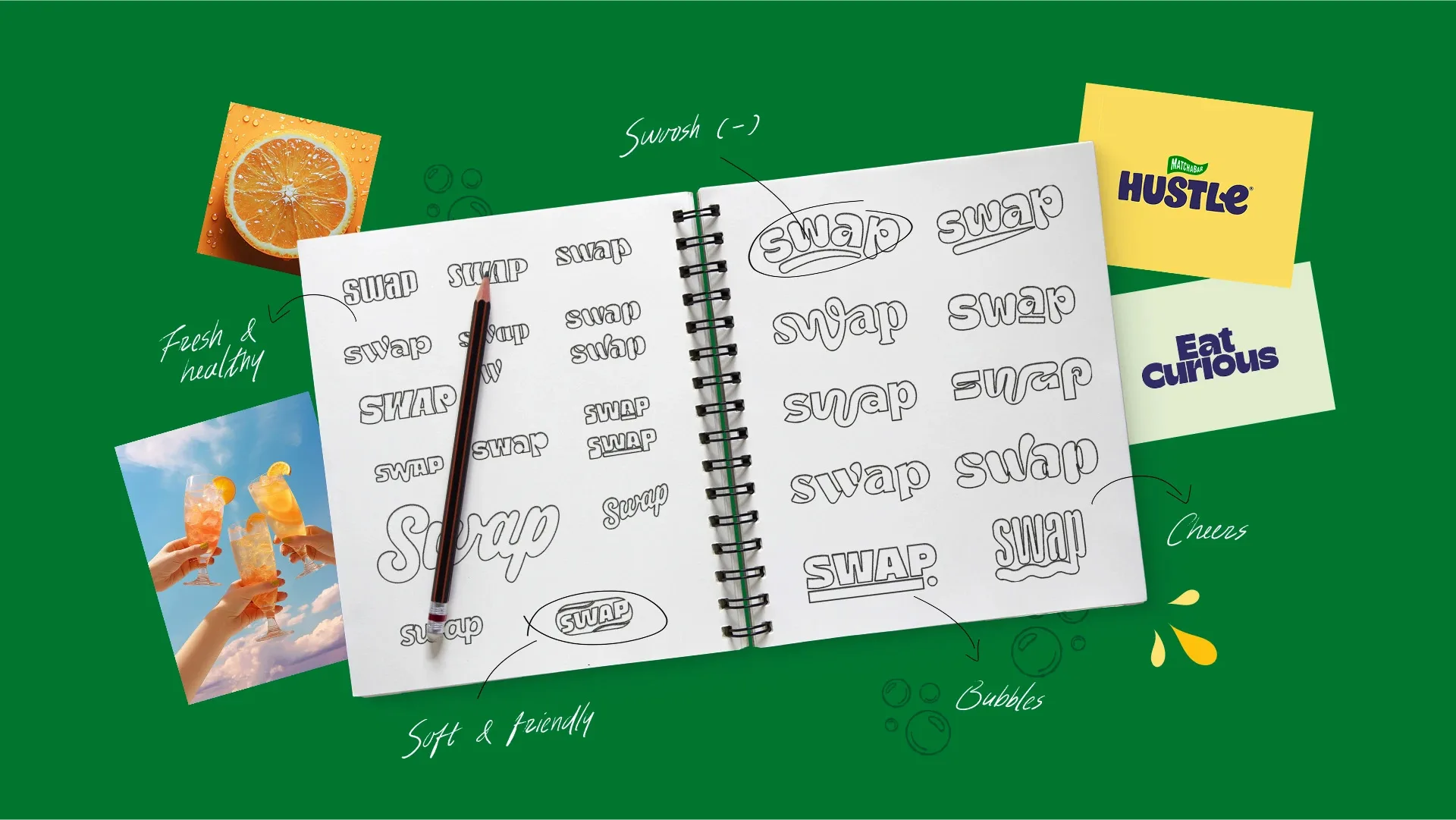
Trong thế giới thiết kế đồ họa, typography không chỉ là việc chọn font chữ đẹp mà còn là nghệ thuật kể chuyện thương hiệu. Đặc biệt trong thiết kế bao bì, font chữ có thể quyết định liệu sản phẩm của bạn có nổi bật trên kệ hàng hay bị chìm vào quên lãng. Năm 2025, typography trong bao bì đang chứng kiến những đổi mới sáng tạo, từ font chữ viết tay cá tính đến serif hiện đại đầy tinh tế. Bạn muốn làm mới website của mình với nội dung hấp dẫn hoặc tìm cảm hứng cho dự án bao bì tiếp theo? Hãy cùng khám phá các xu hướng typography trong thiết kế bao bì và cách áp dụng chúng để tạo dấu ấn thương hiệu mạnh mẽ!
1. Font Chữ Tùy Chỉnh: Tạo Dấu Ấn Độc Quyền
Năm 2025, các thương hiệu lớn đang đầu tư vào font chữ tùy chỉnh để khẳng định bản sắc riêng. Thay vì sử dụng font phổ biến như Helvetica hay Times New Roman, các nhà thiết kế tạo ra font độc quyền, phản ánh cá tính thương hiệu. Ví dụ, Coca-Cola đã sử dụng font viết tay đặc trưng để tạo cảm giác thân thiện, trong khi các thương hiệu mỹ phẩm cao cấp như Chanel ưu tiên font serif thanh lịch để toát lên sự sang trọng.
Mẹo thực hành: Nếu ngân sách hạn chế, bạn có thể chỉnh sửa font có sẵn Glyphs để thêm các chi tiết độc đáo, như đuôi chữ uốn lượn hoặc ký tự cách điệu. Hãy thử font Việt hóa như DVN Qiolany để tạo cảm giác tinh tế và gần gũi với thị trường Việt Nam.
2. Font Chữ Tương Phản: Thu Hút Mọi Ánh Nhìn
Sự tương phản giữa các kiểu font (như kết hợp sans-serif và serif) hoặc kích thước chữ (lớn và nhỏ) đang là xu hướng hot trong thiết kế bao bì. Ví dụ, bao bì cà phê có thể sử dụng font sans-serif đậm cho tên thương hiệu và font script nhẹ nhàng cho mô tả sản phẩm, tạo sự cân bằng giữa mạnh mẽ và tinh tế. Điều này giúp hướng mắt người tiêu dùng đến thông tin quan trọng một cách tự nhiên.
Mẹo thực hành: Khi thiết kế, hãy áp dụng nguyên tắc F-Pattern (đặt chữ lớn ở góc trên bên trái) để tăng tính trực quan. Sử dụng Canva hoặc Adobe Illustrator để thử nghiệm các cặp font tương phản, như Roboto với Playfair Display, và kiểm tra trên mockup bao bì.
3. Font Chữ Viết Tay: Thêm Hồn Vào Bao Bì
Font chữ viết tay mang lại cảm giác thủ công, gần gũi, đặc biệt phù hợp với các sản phẩm hữu cơ, thủ công hoặc địa phương. Trong năm 2025, font viết tay được cách điệu với các đường nét không đều, tạo cảm giác chân thực. Ví dụ, bao bì mứt handmade có thể sử dụng font như MTD Anydore để nhấn mạnh sự mộc mạc và chất lượng tự nhiên.
Mẹo thực hành: Tìm font viết tay Việt hóa trên các trang như fontvn.com hoặc Dafont. Hãy chọn font có hỗ trợ dấu tiếng Việt để tránh lỗi hiển thị. Nếu muốn tự tạo font, thử Calligraphr để chuyển chữ viết tay của bạn thành font kỹ thuật số.
4. Tích Hợp Font Với Hiệu Ứng 3D Và Kết Cấu
Typography trong bao bì không chỉ là chữ phẳng nữa. Năm 2025, các nhà thiết kế sử dụng hiệu ứng 3D, bóng đổ, hoặc kết cấu (texture) để làm chữ nổi bật. Ví dụ, bao bì rượu vang có thể sử dụng font serif với hiệu ứng kim loại ánh vàng, tạo cảm giác cao cấp. Kết cấu như giấy kraft hoặc vải linen cũng được áp dụng để tăng tính chân thực.
Mẹo thực hành: Sử dụng Photoshop để thêm hiệu ứng 3D hoặc kết cấu vào font. Hãy thử các PSD hiệu ứng như “gạch ngang chất” từ fontvn.com để tạo chữ nổi trên bao bì. Đảm bảo hiệu ứng không làm giảm độ dễ đọc của thông tin sản phẩm.
5. Minimalism Với Font Sans-Serif: Sạch Sẽ Và Hiện Đại
Phong cách tối giản vẫn thống trị thiết kế bao bì, với font sans-serif như Montserrat hoặc Poppins được ưa chuộng nhờ sự sạch sẽ và dễ đọc. Các thương hiệu công nghệ hoặc thực phẩm lành mạnh thường chọn font này để truyền tải thông điệp đơn giản nhưng chuyên nghiệp. Ví dụ, bao bì sữa hạt có thể sử dụng font sans-serif mỏng để nhấn mạnh sự nhẹ nhàng và lành mạnh.
Mẹo thực hành: Khi sử dụng font sans-serif, chú ý đến kerning (khoảng cách giữa các chữ cái) và leading (khoảng cách giữa các dòng) để đảm bảo văn bản dễ đọc. Dùng Adobe InDesign để kiểm soát chính xác các thông số này.
6. Font Chữ Hỗ Trợ Tiếng Việt: Tôn Vinh Bản Sắc Văn Hóa
Với thị trường Việt Nam, font chữ hỗ trợ dấu tiếng Việt là yếu tố không thể thiếu. Các font như DVN Deluxy Việt Hóa hoặc SVN Gotham Việt Hóa không chỉ đảm bảo hiển thị đúng mà còn mang lại vẻ đẹp hiện đại, phù hợp cho bao bì sản phẩm nội địa. Năm 2025, các thương hiệu Việt Nam đang ưu tiên font Việt hóa để tạo sự gần gũi với người tiêu dùng.
Mẹo thực hành: Kiểm tra font trên các phần mềm như Word hoặc Photoshop để đảm bảo không có lỗi Unicode. Nếu gặp vấn đề, tham khảo các bài viết về “lỗi font tiếng Việt” trên DesignerVN hoặc tải font Việt hóa trên fontvn.com.
7. Công Cụ Hỗ Trợ Typography Trong Thiết Kế Bao Bì
Để tạo ra bao bì ấn tượng, bạn cần những công cụ phù hợp. Dưới đây là một số gợi ý cho năm 2025: